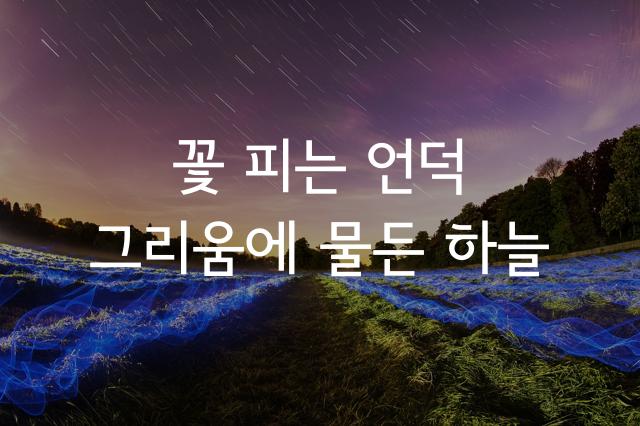
서울한강체는 서울시청에서 제작한 한국어 바탕체 폰트로, 전통적인 서예의 아름다움을 현대적 디자인에 녹여내어 도시의 정체성과 문화적 유산을 표현합니다. 이 폰트는 섬세하면서도 독특한 자태를 자랑하며, 감성적인 디자인을 완성하는 데 적합합니다.
서울한강체은(는)
바탕 스타일 계열의 생김새를 가지고 있으며
웹/앱 디자인, 광고 문구, 소셜 미디어 등에서 자주 활용되며, 효과적인 메시지 전달에 적합합니다.
이 폰트는 광고/마케팅, 문화/예술, 기술/IT 분야에 잘 어울리며,
친근한, 편안한, 재미있는 느낌을 담고 있는 것이 특징입니다.